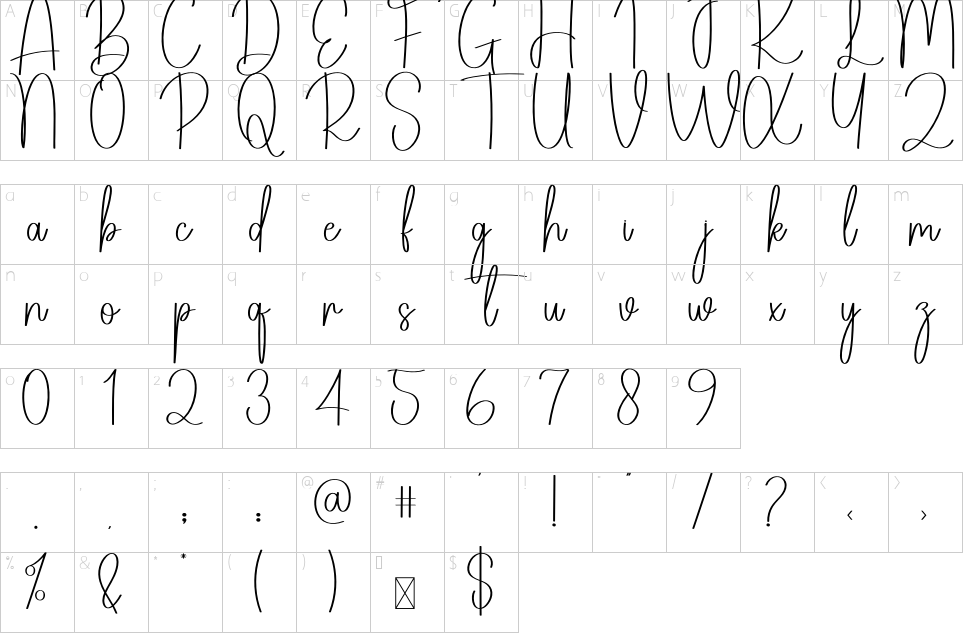
A Georgia é uma elegante fonte que combina perfeitamente para qualquer projeto editorial. Desenhada por scratchones, essa fonte ajuda a criar texto limpo e profissional. Ela vem disponível tanto para Windows quanto para Mac, tornando-a acessível para designers de todo o mundo. Em seu design suave e moderno, a Georgia mantém uma elegância que se sobrepõe à simplicidade, tornando-a uma escolha popular entre criadores de conteúdo. Desde sua criação, mais de 649 pessoas já baixaram esta fonte, um indício de sua popularidade e qualidade. Se você está procurando por uma fonte para trabalhos em que a leitura precisa ser confortável e o design deve ser sofisticado, Georgia é um ótimo opção.